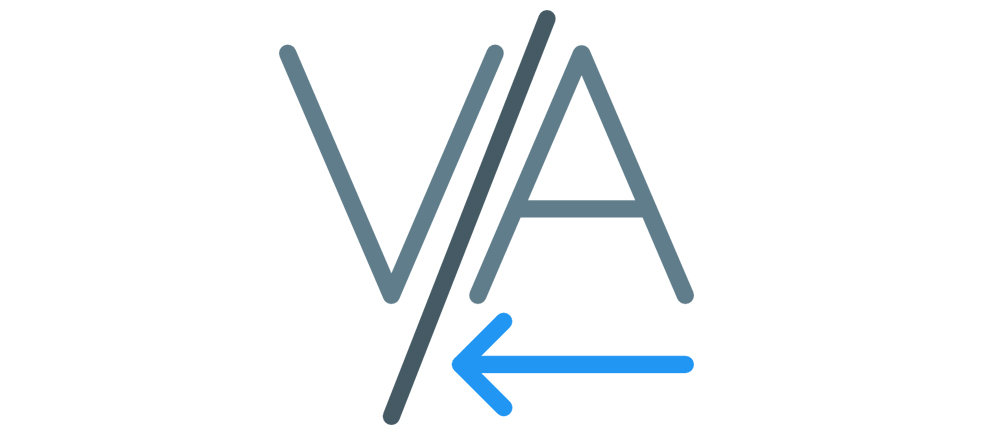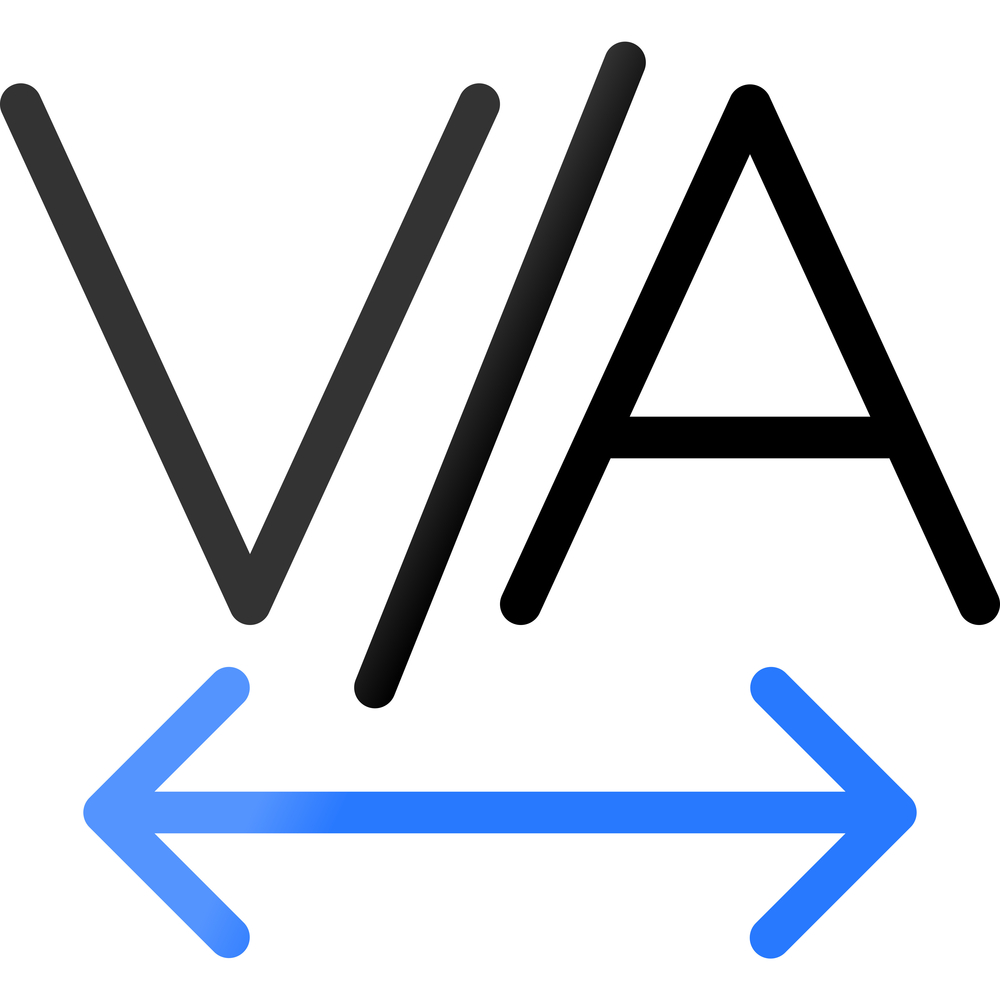
¿Qué es el kerning y el tracking? | Conceptos de tipografía
En el mundo de la tipografía hay multitud de conceptos que pueden resultar confusos cuando se está en el nivel principiante. Hoy veremos dos: kerning y tracking, con sus diferencias y aplicaciones.
En el campo de la tipografía, hay multitud de términos que se pueden confundir cuando aún no se tienen conocimientos avanzados. Hoy tratamos dos de ellos: el kerning y el tracking. Ambos conceptos son fundamentales en el diseño gráfico y editorial, ya que en ambos se trabaja constantemente con tipografías y su legibilidad. Hoy hablaremos de las diferencias entre ambos, pero si quieres dominar la edición para dedicarte profesionalmente a ella, te puede interesar nuestro Máster en Diseño Editorial y Publicaciones Digitales.
¿Qué es el kerning?
El kerning es un término que hace referencia a la modificación del espacio entre dos caracteres específicos que, por sus características, pueden generar problemas de estética en el diseño de la tipografía. Cuando se crea una fuente, cada glifo (signo o carácter) tiene límites predefinidos que determinan el espacio entre ellos. Sin embargo, en ciertos pares de caracteres como "AV" o "Yo", estos espacios pueden resultar visualmente desequilibrados. Por tanto, es necesario ajustarlos mediante el kerning.
En sus inicios, la posibilidad de modificar el kerning estaba limitada exclusivamente a los diseñadores de tipografías. Pero con el paso del tiempo, esta herramienta se democratizó gracias a programas de edición como QuarkXPress e InDesign. Desde finales del siglo pasado, permiten a los usuarios ajustar el kerning manualmente o crear tablas específicas para personalizar el espaciado entre caracteres. Fue así como el kerning se convirtió en una herramienta versátil y accesible, tanto para diseñadores gráficos como tipográficos.
Hoy en día, los programas de diseño ofrecen opciones todavía más flexibles para ajustar el kerning. Por ejemplo, en InDesign se pueden hacer ajustes automáticos basados en configuraciones predeterminadas, modificaciones manuales muy concretas o incluso desactivar el kerning en una tipografía en particular.
No obstante, hay que tener en cuenta que los cambios en el kerning, igual que sucede con el tracking, que veremos ahora, son temporales. Es decir, que están diseñados para adaptarse a las necesidades específicas de cada proyecto.
¿Qué es el tracking?
El tracking es la modificación del espacio entre todos los caracteres de un texto o una palabra de una tipografía. Este espacio, al que se conoce como prosa, es un atributo que quien ha diseñado la fuente determina. Sin embargo, gracias al tracking, se puede ajustar de forma temporal para ajustarlo a las necesidades de cada proyecto.
En español, se le llama también interletrado o interletraje, y se puede ajustar con programas de edición como InDesign o Pagemaker. Es decir, que hay total flexibilidad para aumentar o reducir este espacio.
Cuando el tracking se usa para aumentar el espacio entre los caracteres, se le llama tracking positivo; y cuando es para reducir, tracking negativo. Estos ajustes no son permanentes ni universales, sino que se aplican caso por caso, en función de los requisitos específicos que cada diseño tenga. La finalidad del tracking es mejorar la legibilidad del texto, ya sea en pantalla como en material impreso, y optimizar la presentación visual y la funcionalidad en diferentes formatos. Hay que recordar que cada tipografía tiene una psicología detrás.
A diferencia del kerning, que se centra en ajustar el espacio entre pares específicos de caracteres, el tracking afecta a la distribución del espacio entre todos los caracteres de un texto de manera uniforme. Ambos conceptos son esenciales en el diseño tipográfico, puesto que consiguen que las composiciones sean equilibradas y estéticamente agradables.
Diferencia de kerning y tracking
Como hemos dicho, el kerning y el tracking son esenciales en tipografía, pero se utilizan para finalidades diferentes. El primero se aplica cuando dos caracteres específicos, como en los pares "To" o "Wa", tienen un espacio entre ellos que resulta incómodo a la vista. Con este sencillo ajuste, se equilibra la relación individual entre los caracteres y la estética resulta más agradable.
Por el contrario, el tracking se usa para modificar el espaciado global de un texto completo o de palabras específicas. Por ejemplo, si estamos diseñando un cartel, se suele aumentar el tracking en los títulos para crear una sensación de amplitud y elegancia. Sin embargo, en los cuerpos de texto pequeños se puede reducir ligeramente para mejorar la legibilidad de la tipografía.
Tipos de kerning
Ya hemos visto que el kerning consiste en modificación del espacio entre caractertes. Pero lo que quizás no sabías, es que hay diferentes tipos; cada uno con sus ventajas y aplicaciones concretas. Vamos a verlos.
Kerning automático
El kerning automático el que usa valores predefinidos que han sido establecidos por el diseñador de la tipografía. Estos ajustes van integrados en la fuente y se aplican automáticamente al usar programas de edición, como InDesign o Photoshop.